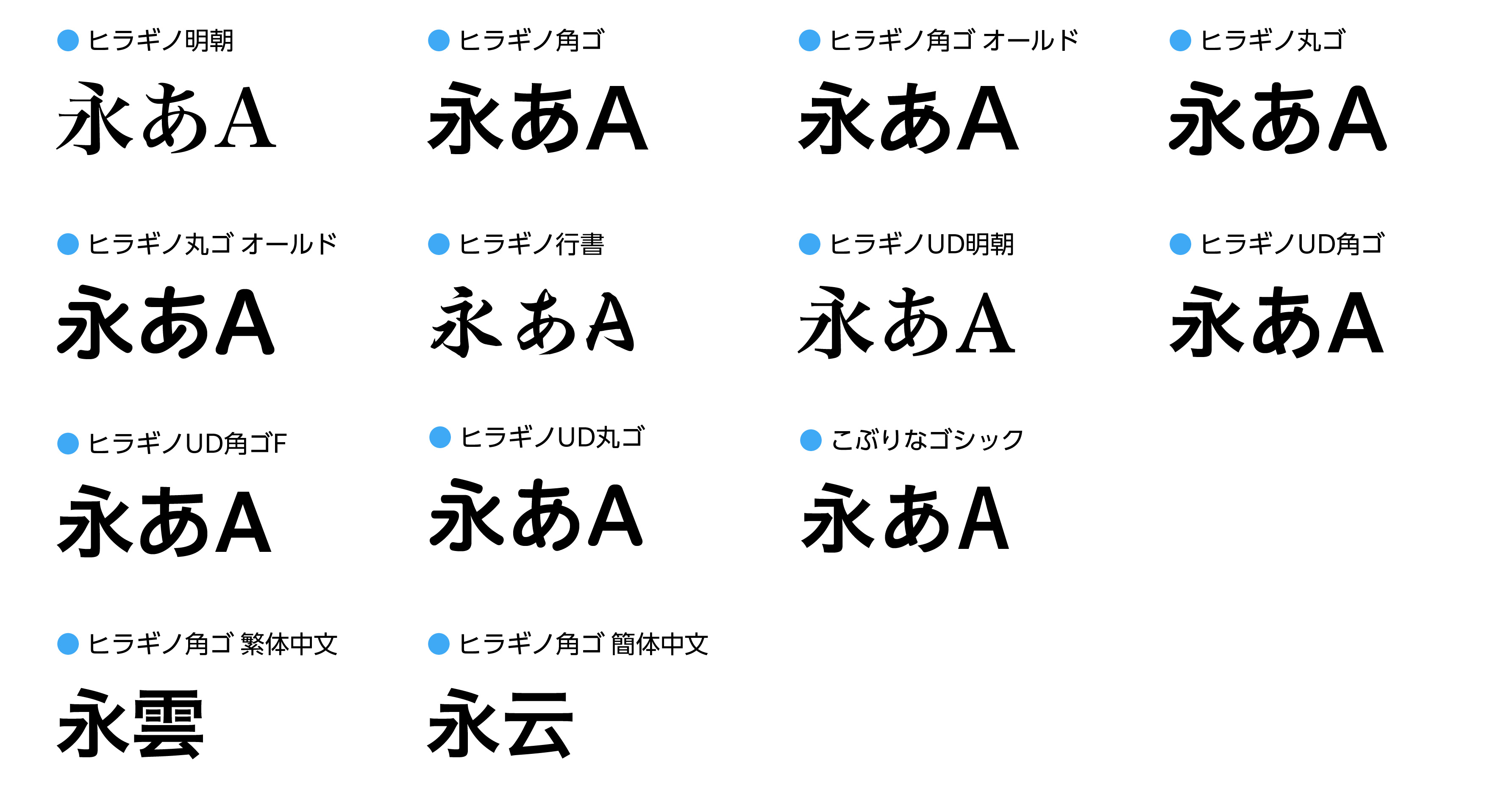
Morisawa サーバーフォントライセンスに株式会社SCREENグラフィックソリューションズの「ヒラギノフォント」を追加
株式会社モリサワは「Morisawa サーバーフォントライセンス」において、株式会社SCREENグラフィックソリューションズの「ヒラギノフォント63書体」を追加します。
クラウド型のフォントサブスクリプションサービス「Morisawa Fonts」で提供しているヒラギノフォントをサーバー環境で利用可能なフォントラインナップとして拡充し、多様化するデジタル制作環境において、より柔軟なフォント運用を支援します。
今回追加するヒラギノフォントは、画像と調和しながら、くっきりと読みやすいデザインを特長とし、請求書・納品書などの帳票生成から広告バナー、自動組版、Web to Printまで、多様な成果物において美しさと可読性を両立します。
提供書体
ヒラギノ明朝 |
W2 / W3 / W4 / W5 / W6 / W7 / W8 |
ヒラギノ角ゴ |
W0 / W1 / W2 / W3 / W4 / W5 / W6 / W7 / W8 / W9 |
ヒラギノ角ゴ オールド |
W6 / W7 / W8 / W9 |
ヒラギノ丸ゴ |
W2 / W3 / W4 / W5 / W6 / W7 / W8 |
ヒラギノ丸ゴ オールド |
W4 / W6 / W8 |
ヒラギノ行書 |
W4 / W8 |
ヒラギノUD明朝 |
W4 / W6 |
ヒラギノUD角ゴ |
W3 / W4 / W5 / W6 |
ヒラギノUD角ゴF |
W3 / W4 / W5 / W6 |
ヒラギノUD丸ゴ |
W3 / W4 / W5 / W6 |
こぶりなゴシック |
W0 / W1 / W3 / W6 / W9 |
ヒラギノ角ゴ 繁体中文 |
W3 / W6(Adobe-CNS1-6) |
ヒラギノ角ゴ 簡体中文 |
W3 / W6(Adobe-GB1-6) |
ヒラギノ角ゴ 簡体中文 Std |
W0 / W1 / W2 / W3 / W4 / W5 / W6(Adobe-GB1-0) |